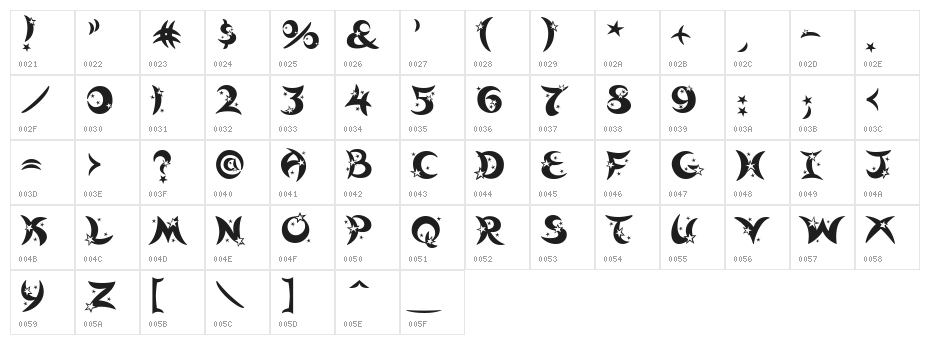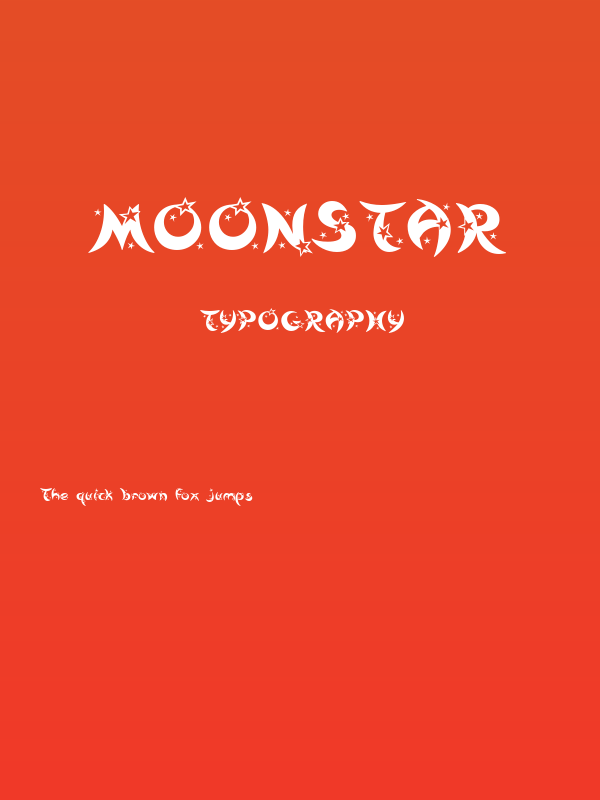
Moonstar Font
| Proiecte propuse | Ideal for children's book covers, fantasy-themed event invitations, astrology blogs, or any project needing a magical touch. |